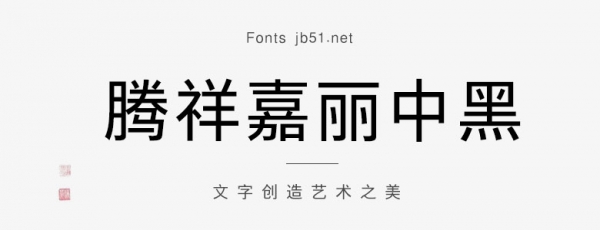
騰祥嘉麗中黑GB18030是一款不錯的藝術(shù)字體,由騰祥字庫出品,該字體字型端正,重心平穩(wěn),布白均勻,適合應(yīng)用于藝術(shù)設(shè)計、平面宣傳設(shè)計、網(wǎng)頁設(shè)計,書法字帖等領(lǐng)域,需要的朋友可以前來本站下載。
騰祥嘉麗黑體系列字庫為騰祥公司早期自行開發(fā)的傳統(tǒng)黑體字庫。字體風(fēng)格采用橫豎筆畫無襯線裝飾的設(shè)計,融入英文設(shè)計元素。字型端正,重心平穩(wěn),布白均勻。本款字體為騰祥嘉麗黑體系列中等粗細一款,介于大黑與細黑之間,適用于小標題及正文排版。